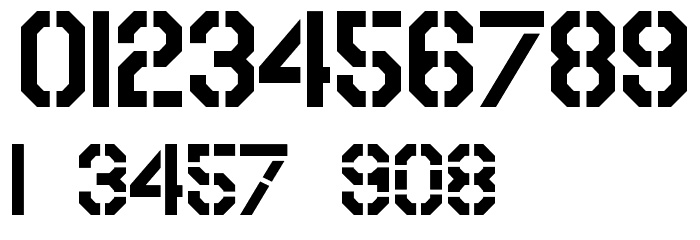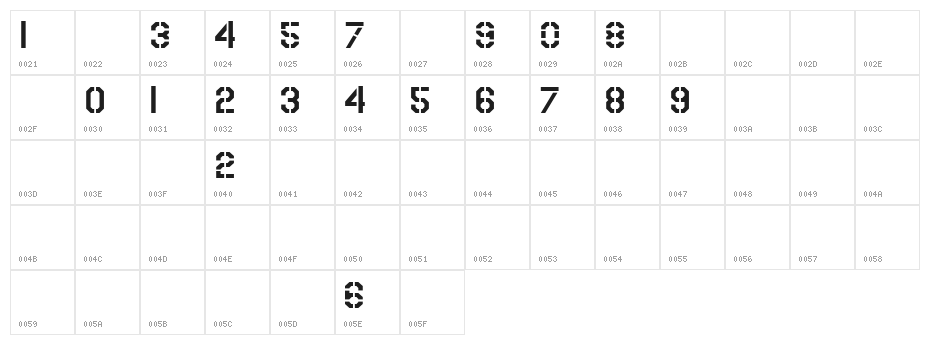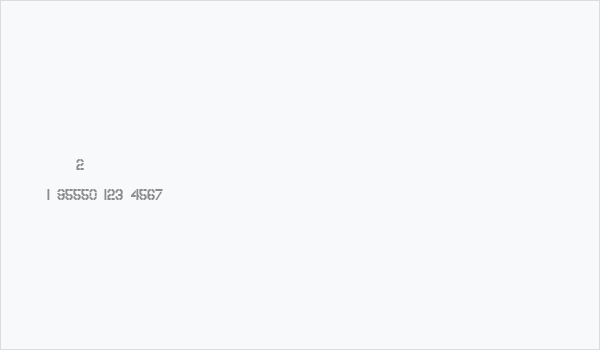
USAAF_Serial_Stencil Font
✎ Stencil
| Categorii | Stencil |
| Stil general | Industrial, Military |
| Caz de utilizare | Signage, Branding, Posters |
| Proiecte propuse | Ideal for military-themed designs, industrial branding, signage, and any project requiring a strong, authoritative typeface. |